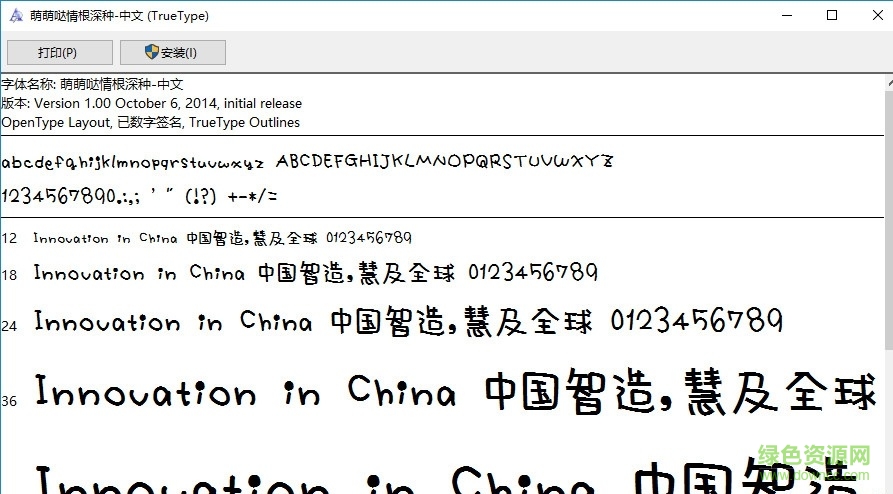
萌萌噠情根深種字體是一款超級(jí)有趣又可愛(ài)的字體,很多女孩子都非常喜愛(ài)這類字體哦,有需要的朋友就來(lái)綠色資源網(wǎng)下載吧!
萌萌噠情根深種字體是一款可愛(ài)創(chuàng)意類型的字體,它能夠?yàn)橛脩籼峁┲杏⑽碾p語(yǔ)字體。該字體具有童趣的手寫(xiě)風(fēng)格,你可以將其用于海報(bào)設(shè)計(jì)、涂鴉設(shè)計(jì)等方面。